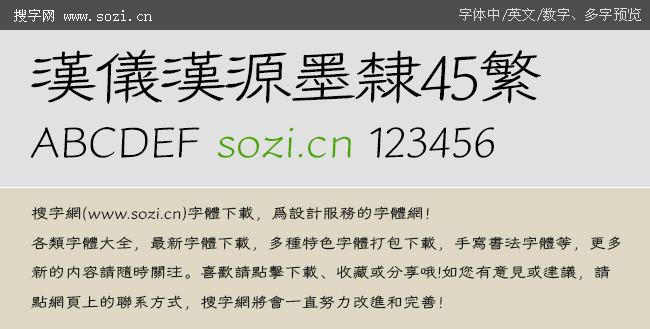
汉仪汉源墨隶45繁
搜字网给大家提供一款汉仪汉源墨隶45繁中文字体下载,汉仪汉源墨隶以现代设计手法重新演绎古老的帛书字体,朴素自然、古雅生动,气质简约明快。书体介乎于篆隶之间,扁平取势,略微向上倾斜,结构紧密,规整之中流露放恣之色。给人以含蕴圆厚之感;细款飘逸灵动,线条轻盈而不失纤韧。适用于画册设计、海报设计、包装设计等场合使用。(本字体为个人非商用版,如需要商用请联系汉仪公司购买版权)